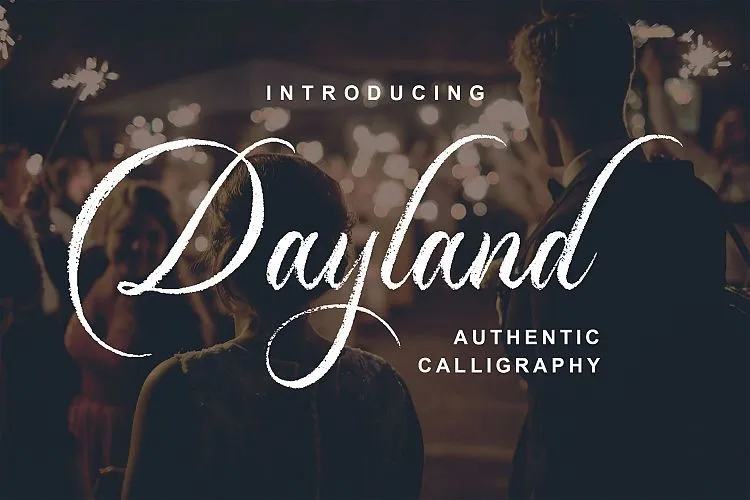
Dayland Calligraphy Font – Download Grátis
Introduzimos a fonte Dayland. Esta é uma nova fonte de script moderna com uma linha base irregular. Ela tem um estilo trendy e feminino. Espero que você goste desta fonte e desses adicionais, tornando-se uma ótima adição à sua coletânea de fontes! A fonte foi projetada e compartilhada pelo Blankids. Dayland é perfeitamente adequada para assinaturas de logotipo, convites de casamento, citações românticas, logotipos, posters, kits para mídia social, capas de livros, design de camisetas e embalagens, entre outros.